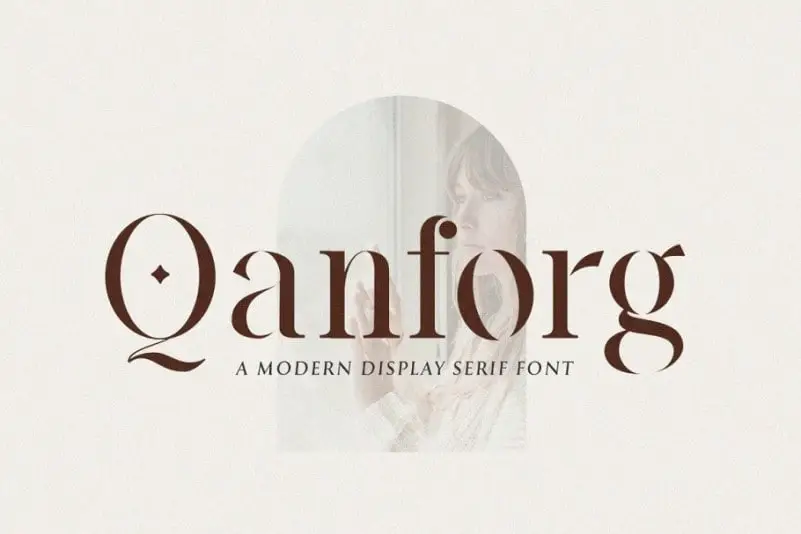
A Qanforg Serif é uma fonte serif que traz uma aparência mais luxuosa aos seus projetos por causa do seu traço fino. Este estilo moderno e minimalista oferece um toque refinado, ideal para uso nos títulos, logotipos ou até mesmo em convites de casamento. Ela também é particularmente adequada para aplicações onde há necessidade de uma serif mais expressiva, proporcionando linhas arredondadas atraentes e formas únicas que adicionam um toque especial à sua designação. Inspirada pelo designer Fionà & Co em 99designs, esta fonte é perfeita para quem procura uma opção elegante para complementar suas criações gráficas.